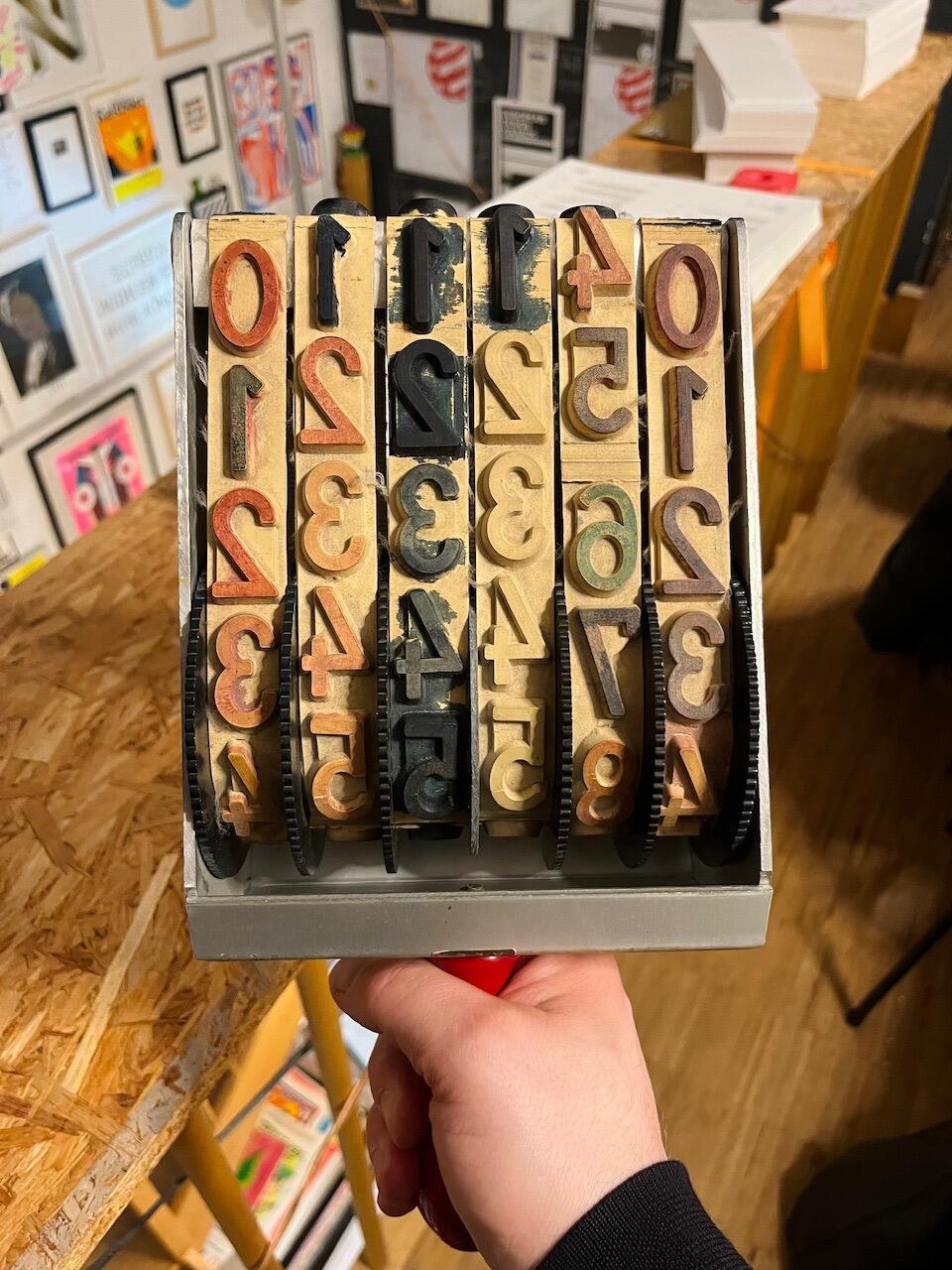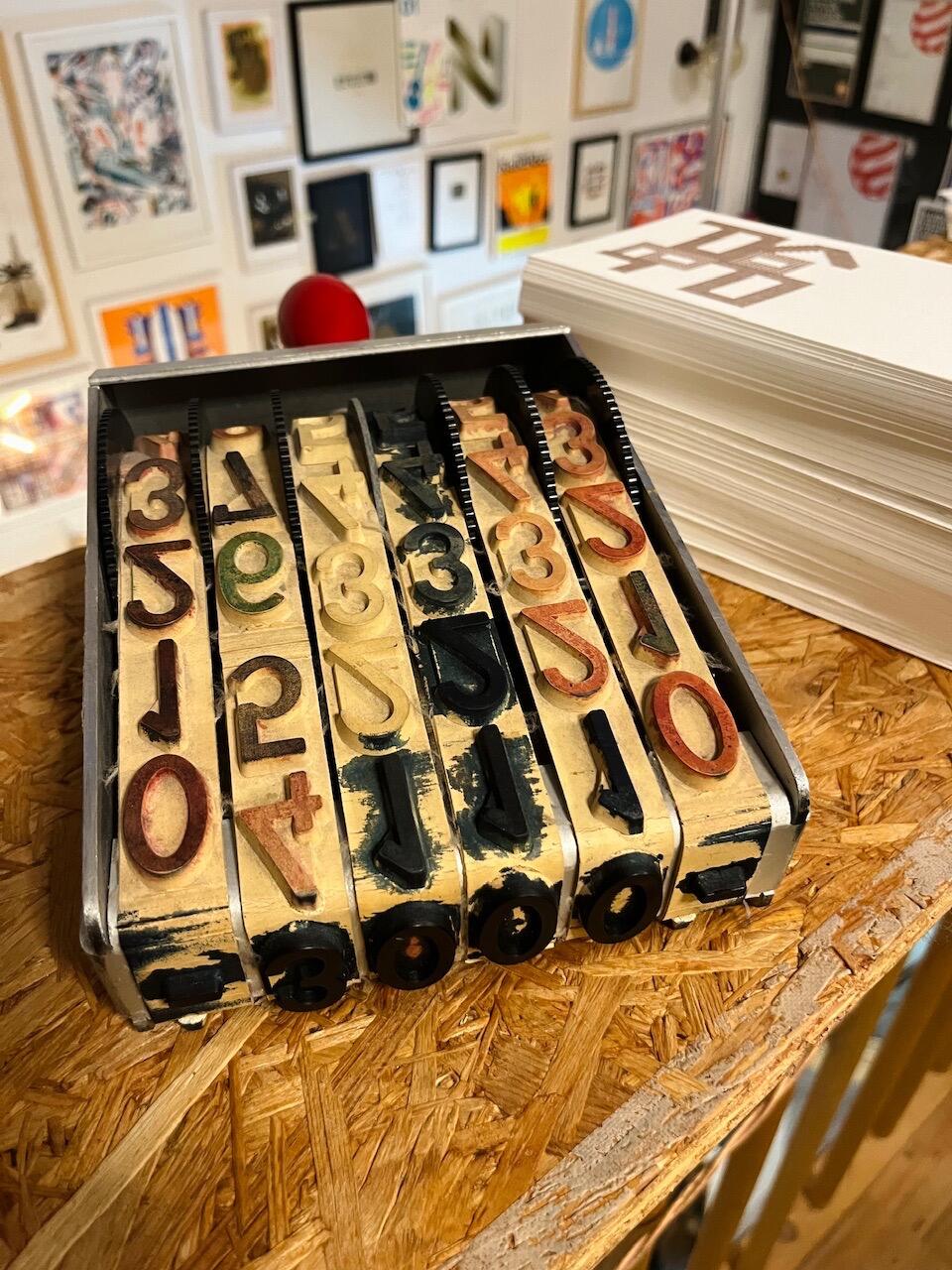
Ach, niedlich 🤓
Hätte nicht gedacht, dass Helvetica sich so gut mit ihrem Klon Arial versteht, aber sie sind wohl aus ihrer kindlichen Rivalität heraus gewachsen… und Courier ist perfekt getroffen. 😁
Dann ist mir im Wappen ein verstecktes G aufgefallen.
Versteckt?:aschehaupt:
Mir ist das G bis vor Kurzem auch nie aufgefallen, obwohl mir das Wappen schon sehr lange geläufig ist. :aschehaupt:
Really? Für mich, der mit Fußball nichts am Hut hat, war das G immer da. Man fragt sich doch unweigerlich was für eine Form das um S04 herum ist oder? Aber selbst wenn man es nicht sieht ist es zumindest nicht »versteckt«.
Dabei heißt der Verein doch FC Gelsenkirchen-Schalke …
Ja; im Sprachgebrauch ist allerdings nur (FC) Schalke 04 bzw. die Kurzform S04. Da erwartet man nicht zwangsläufig ein G im Wappen.
Versteckt ist es sicher nicht, aber aufgrund der Formgebung auch nicht sonderlich offensichtlich. Für mich ist das wie ein Kippbild: Die einen sehen es sofort und andere nur dann, wenn man sie darauf hinweist.
Für die, die es angeht, ist es meines Erachtens schon offensichtlich. Als Gelsenkirchner ist man Schalke-Fan, dann weiß man wo man herkommt und sieht das G. Alle anderen interessieren sich entweder nicht für Fußball oder nicht für Schalke, die sehen noch nicht mal das Logo.
Die Mainzer werden wissen, dass das ein M sein soll. Die anderen …
Ja, da macht es uns der DFB Schon leichter. Der hat gleich das ganze Alphabet (und nicht nur das lateinische) in seinem Logo versteckt.
ist auch direkt integriert
Der DFB steht auch auch für Freude durch Kraft! (scnr)
Hab eine Sekunde gebraucht:
Ein Klassiker in Wien.
Dieses Schild hätte auch Potenzial gehabt, nur wurde es inzwischen anscheinend ausgebessert …
Ich mach mal weiter mit großer Typo …
Interessante Mischung aus DIN (3, 4 und 7) und die sog. Spitze Ziffern der Bahn-Futura (0, 2) von Theodor Dierksmeier, eine für die Deutsche Bundesbahn nachkonstruierte Version der Futura. Aber dann mit abgerundete Ecken. Hast du eine Idee, wozu dieses Ding (ein riesiger Numeroteur?) verwendet wurde?